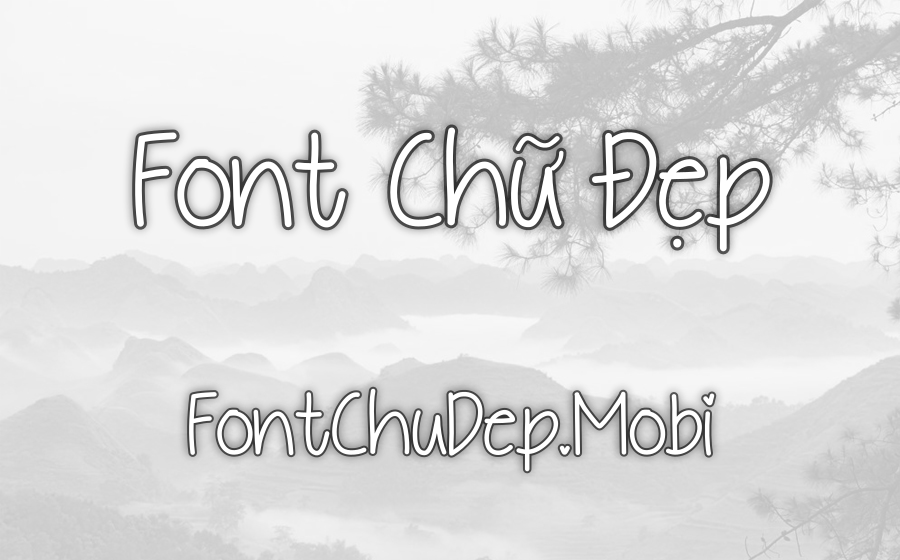
UVF Daddy’s Girl là một font chữ viết tay đầy sức hút, thể hiện phong cách nữ tính và sự tinh nghịch độc đáo. Khi bạn nhìn vào những đường nét mềm mại và uyển chuyển của font chữ này, cảm giác thân thiện và ấm áp dường như lan tỏa ngay lập tức. Đây là lựa chọn lý tưởng cho những ai đang tìm kiếm một kiểu chữ để thiết kế thiệp mời, bao bì sản phẩm, logo, hay các ấn phẩm dành cho trẻ em. Font chữ này đã được thành viên của FontChuDep.mobi cẩn thận sưu tầm và chia sẻ, khiến mình có thêm niềm tin vào chất lượng tuyệt vời mà nó mang lại. Cảm giác khi sử dụng UVF Daddy’s Girl thật sự rất tuyệt vời, khi nó không chỉ làm nổi bật thiết kế của bạn mà còn truyền tải được cảm xúc một cách trọn vẹn.
Font UVF Daddysgirl Việt Hóa
UVF Daddys Girl